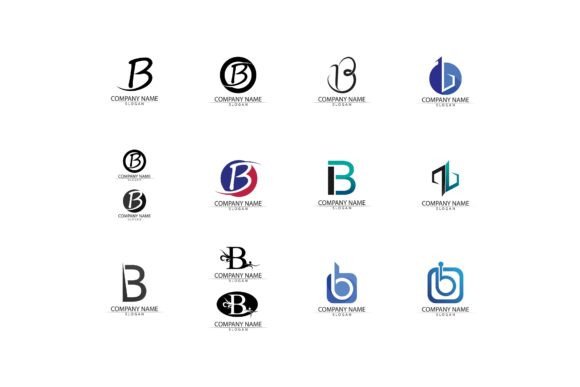
B Font and Letter Logo Design Vector
Die richtigen Designelemente zu finden, kann eine Herausforderung sein, aber B Font and Letter Logo Design Vector bietet eine außergewöhnliche Sammlung, die Ihre Arbeit sofort aufwertet.
Egal, ob Sie POD-Produkte (Print on Demand), Hochzeitseinladungen oder Social-Media-Grafiken erstellen, B Font and Letter Logo Design Vector ist die ideale Wahl.